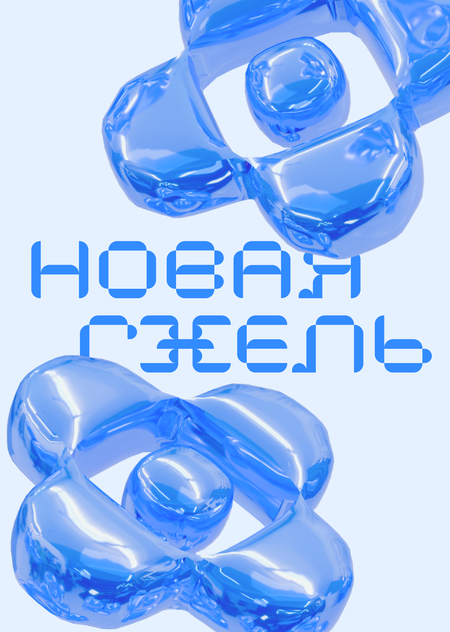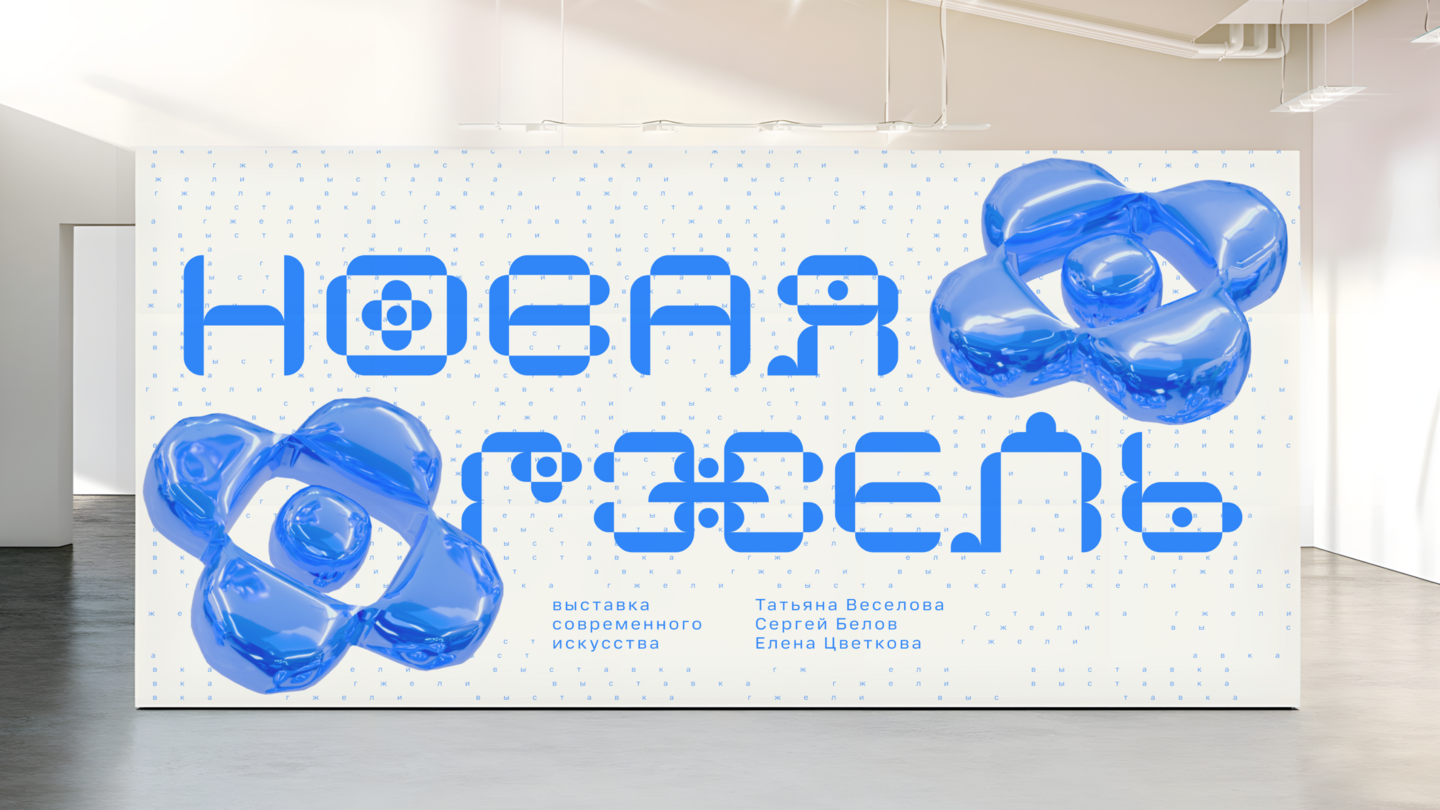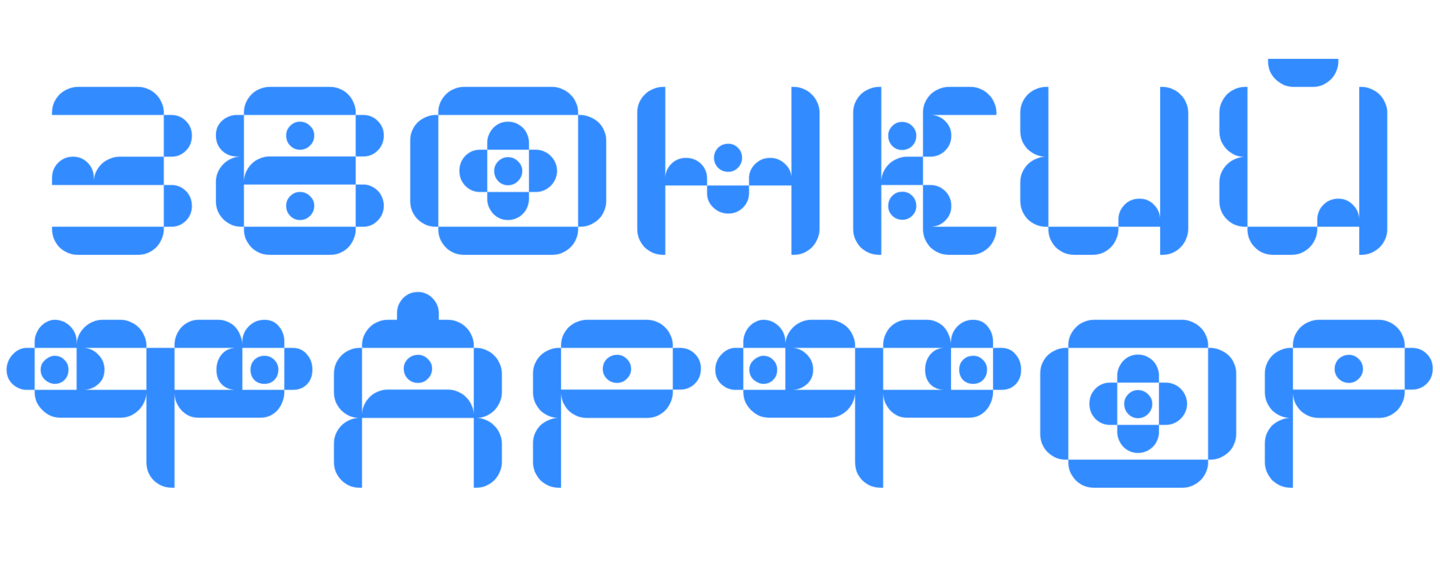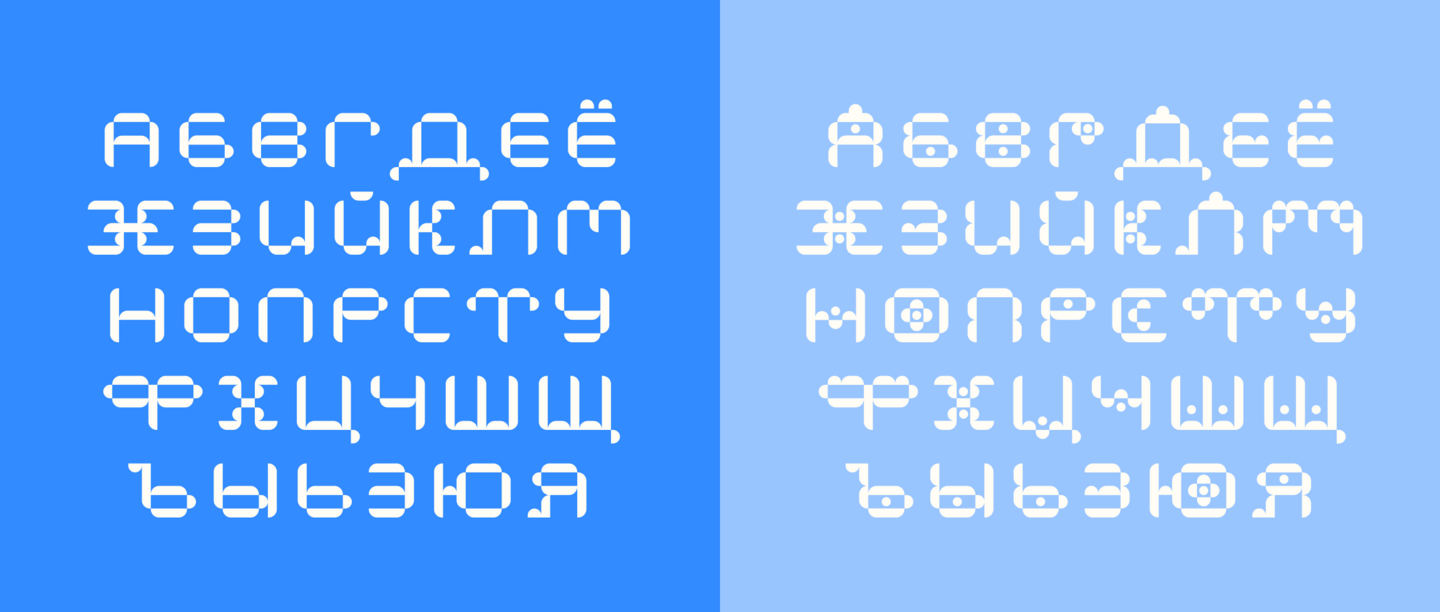
Выставка «Новая Гжель» представляет работы современных художников, переосмысляющих традиции гжельского промысла. В экспозиции исследуется трансформация характерных элементов — формы, цвета и орнамента — через использование новых материалов, технологий и художественных практик
В основу айдентики выставки лег фирменный шрифт «Гжель», построенный на цветочных орнаментах гжельской росписи, которая обретает лаконичную пластику в современной интерпретации